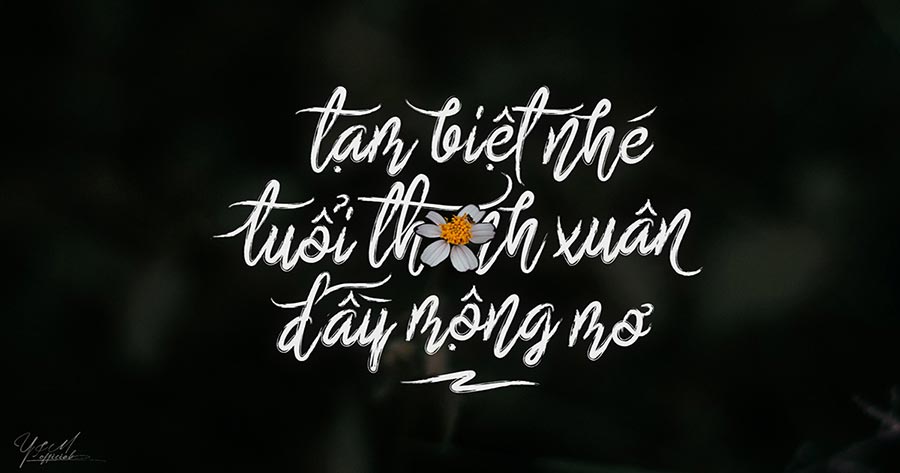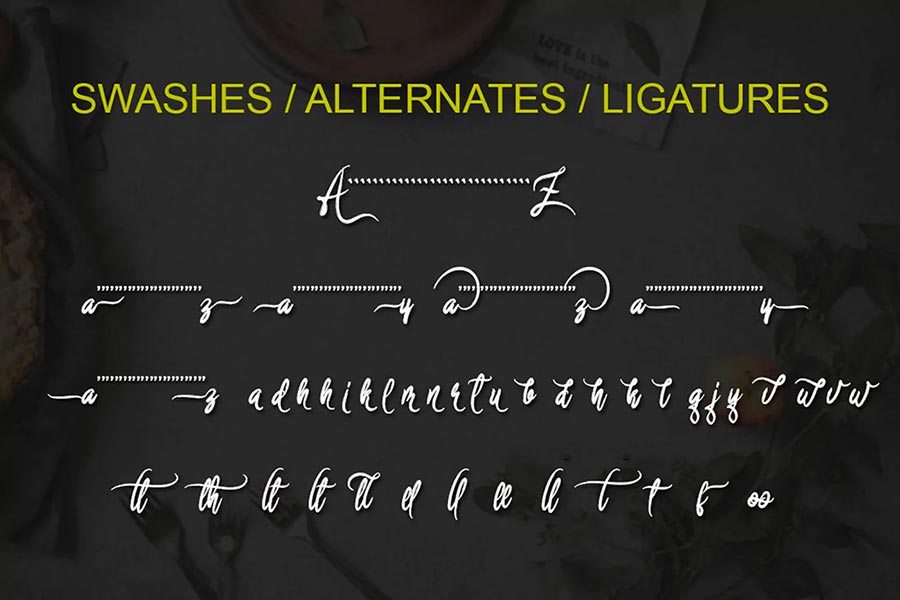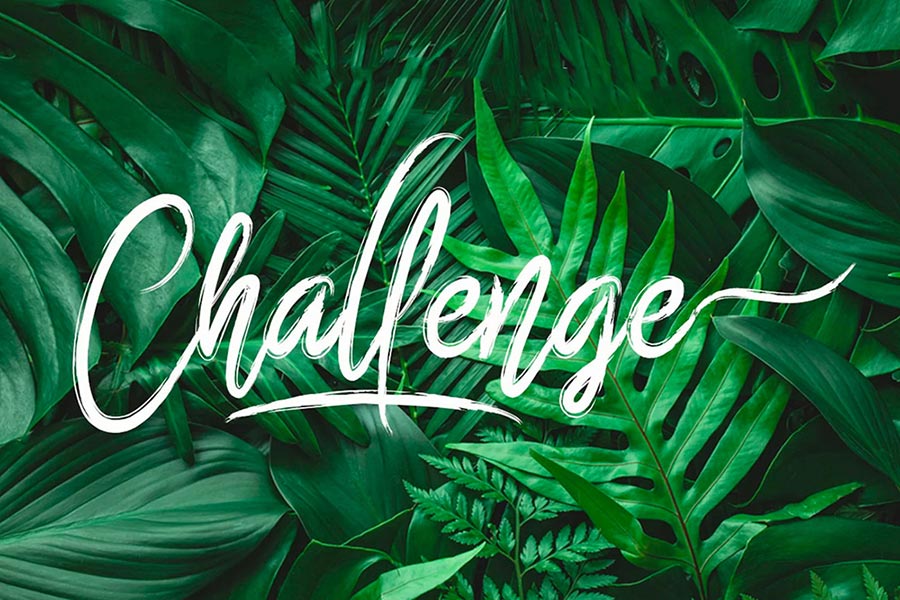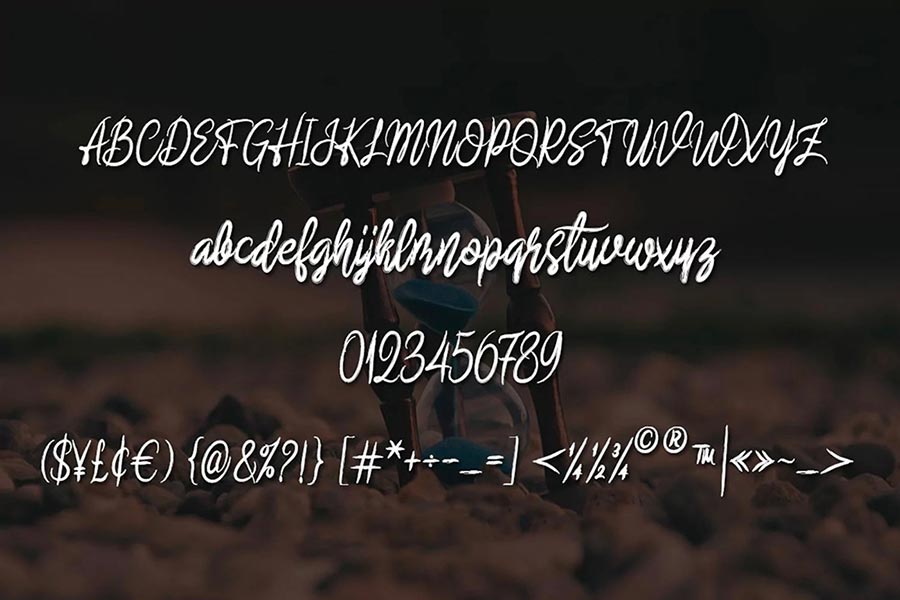
Chia Sẻ Miễn Phí Font Việt Hóa - Fathan Nét Bút Lông Mang Phong Cách Cổ Điển
Font chữ đóng vai trò quan trọng trong việc tạo nên bản sắc và sức hút cho các thiết kế đồ họa. Với những nhà thiết kế, việc tìm kiếm các bộ font độc đáo, mang tính ứng dụng cao luôn là một ưu tiên hàng đầu. Trong bài viết hôm nay, Sadesign giới thiệu đến bạn một bộ font Việt hóa miễn phí mang tên Fathan, với phong cách bút lông cổ điển, chắc chắn sẽ là lựa chọn lý tưởng cho nhiều dự án sáng tạo.
Font Fathan - Nét Đẹp Cổ Điển Trong Từng Nét Chữ
Font Fathan được thiết kế với phong cách bút lông mềm mại, uyển chuyển nhưng không kém phần mạnh mẽ. Điểm đặc biệt của bộ font này nằm ở sự kết hợp tinh tế giữa nét chữ cổ điển và tính hiện đại, tạo nên cảm giác vừa gần gũi vừa mới lạ. Đây là loại font lý tưởng để sử dụng trong các thiết kế mang hơi hướng vintage, retro hay các dự án yêu cầu sự sang trọng và tinh tế.
Đặc Điểm Nổi Bật Của Font Fathan
1. Phong cách bút lông cổ điển: Font Fathan tái hiện hoàn hảo nét viết tay bằng bút lông, mang đến cảm giác mềm mại, tự nhiên trong từng đường nét.
2. Hỗ trợ tiếng Việt đầy đủ: Bộ font đã được Việt hóa hoàn chỉnh, đảm bảo tương thích với tất cả các ký tự tiếng Việt, từ dấu sắc, huyền, hỏi, ngã cho đến nặng.
3. Tính ứng dụng cao: Font Fathan phù hợp với nhiều loại hình thiết kế như poster, logo, thiệp mời, hoặc các ấn phẩm quảng cáo mang phong cách cổ điển.
Font Fathan không chỉ là một bộ font Việt hóa miễn phí mà còn là một công cụ tuyệt vời để nâng tầm các thiết kế của bạn. Với phong cách bút lông cổ điển đầy cuốn hút, Fathan hứa hẹn sẽ mang đến nguồn cảm hứng sáng tạo mới mẻ cho các nhà thiết kế đồ họa.